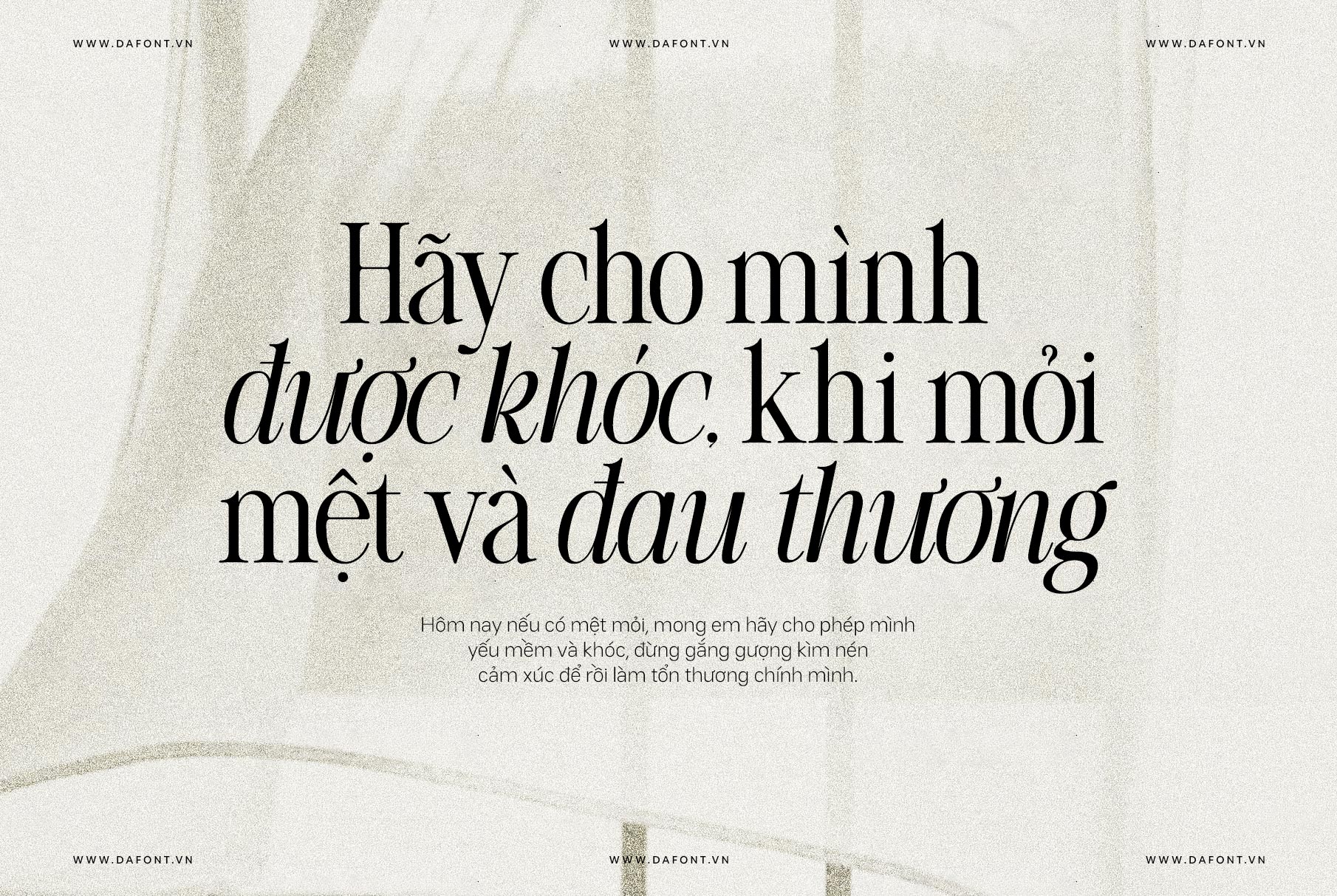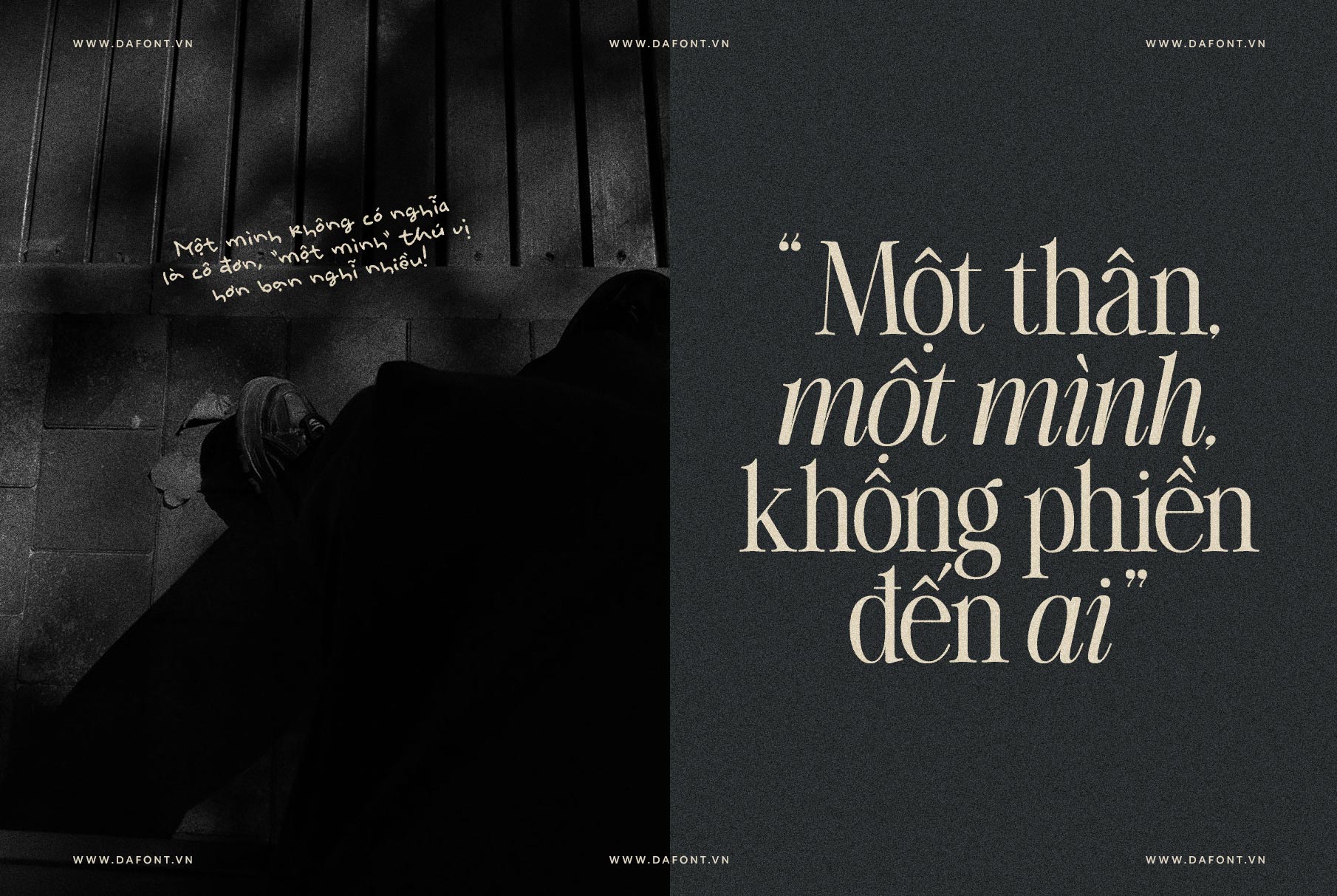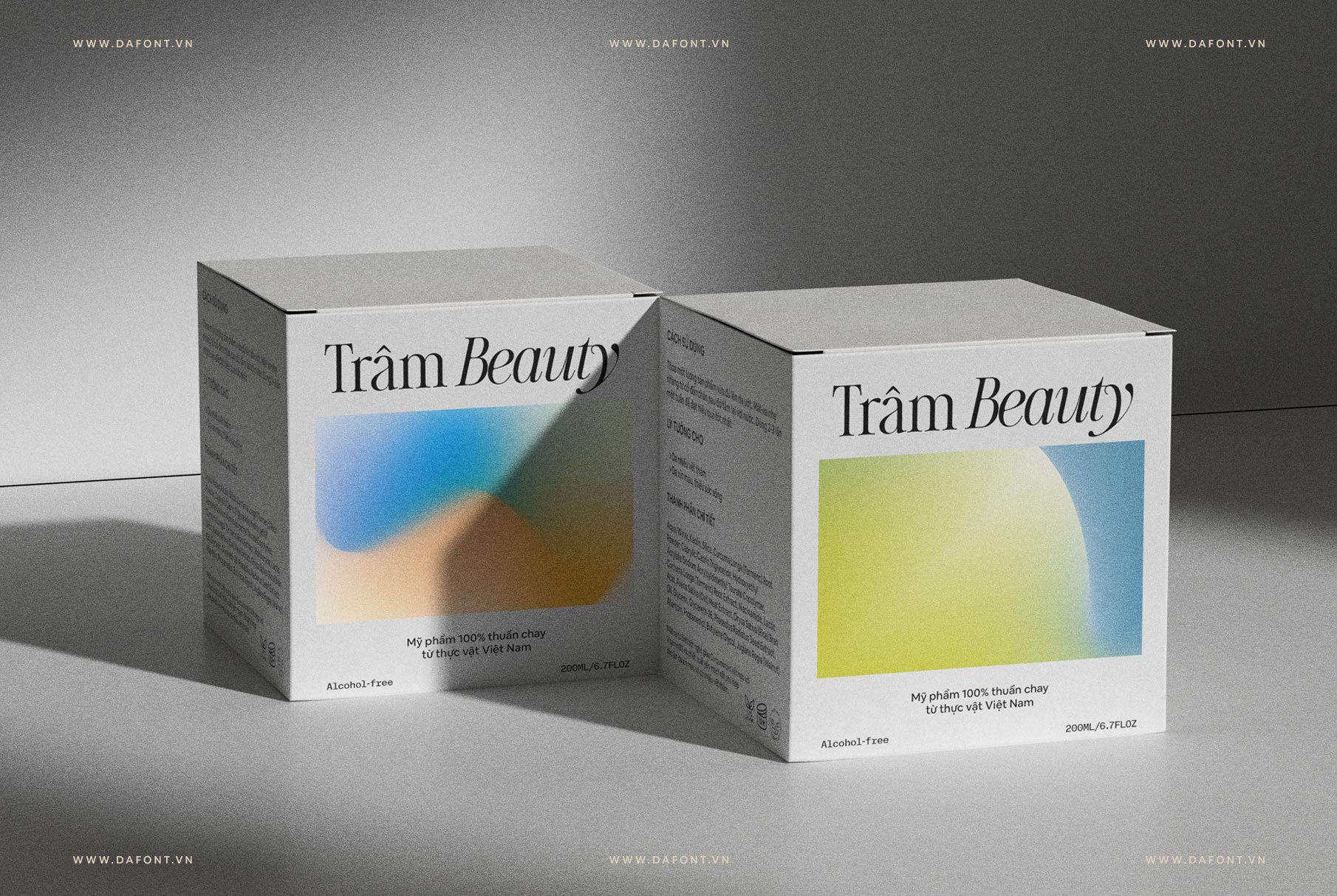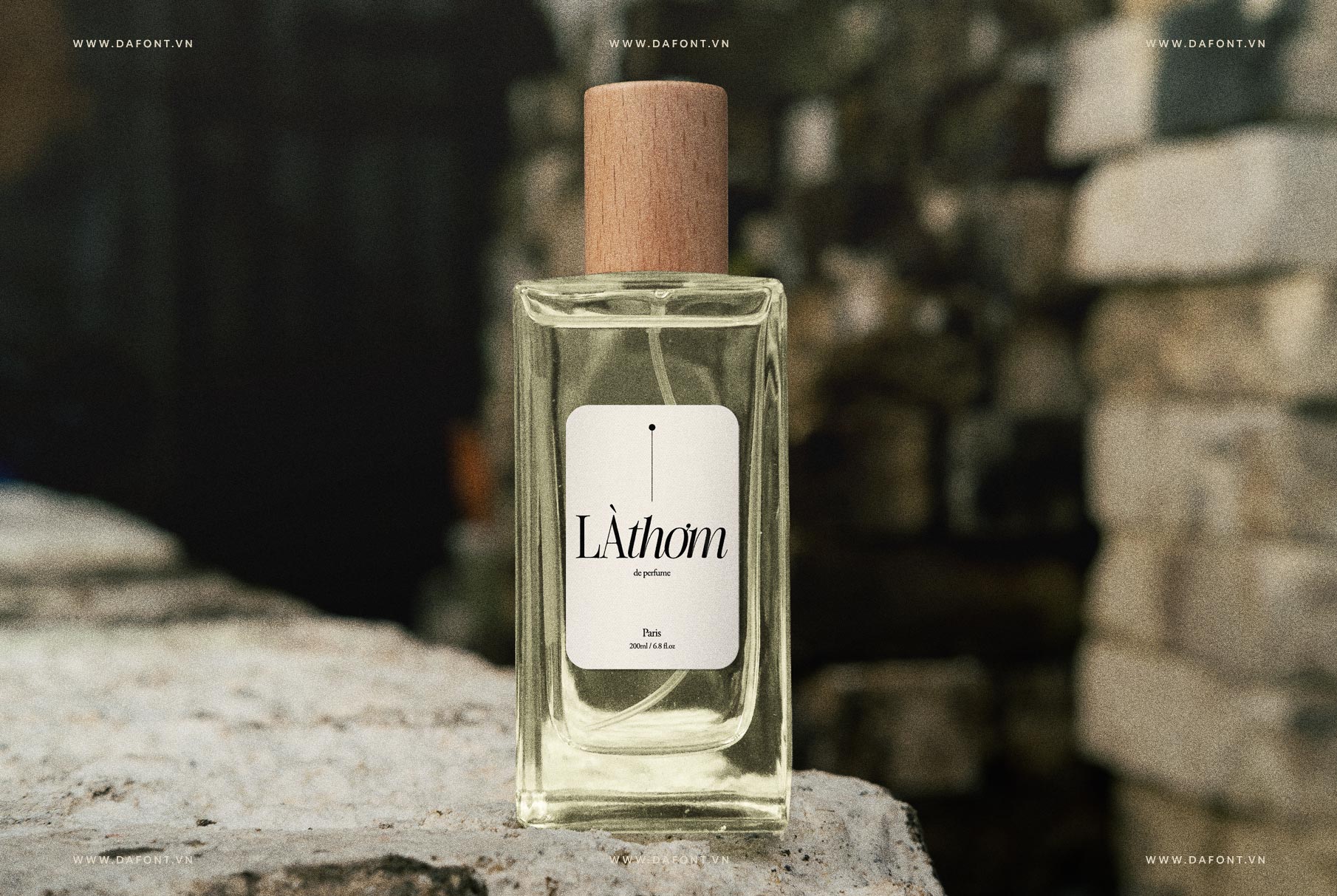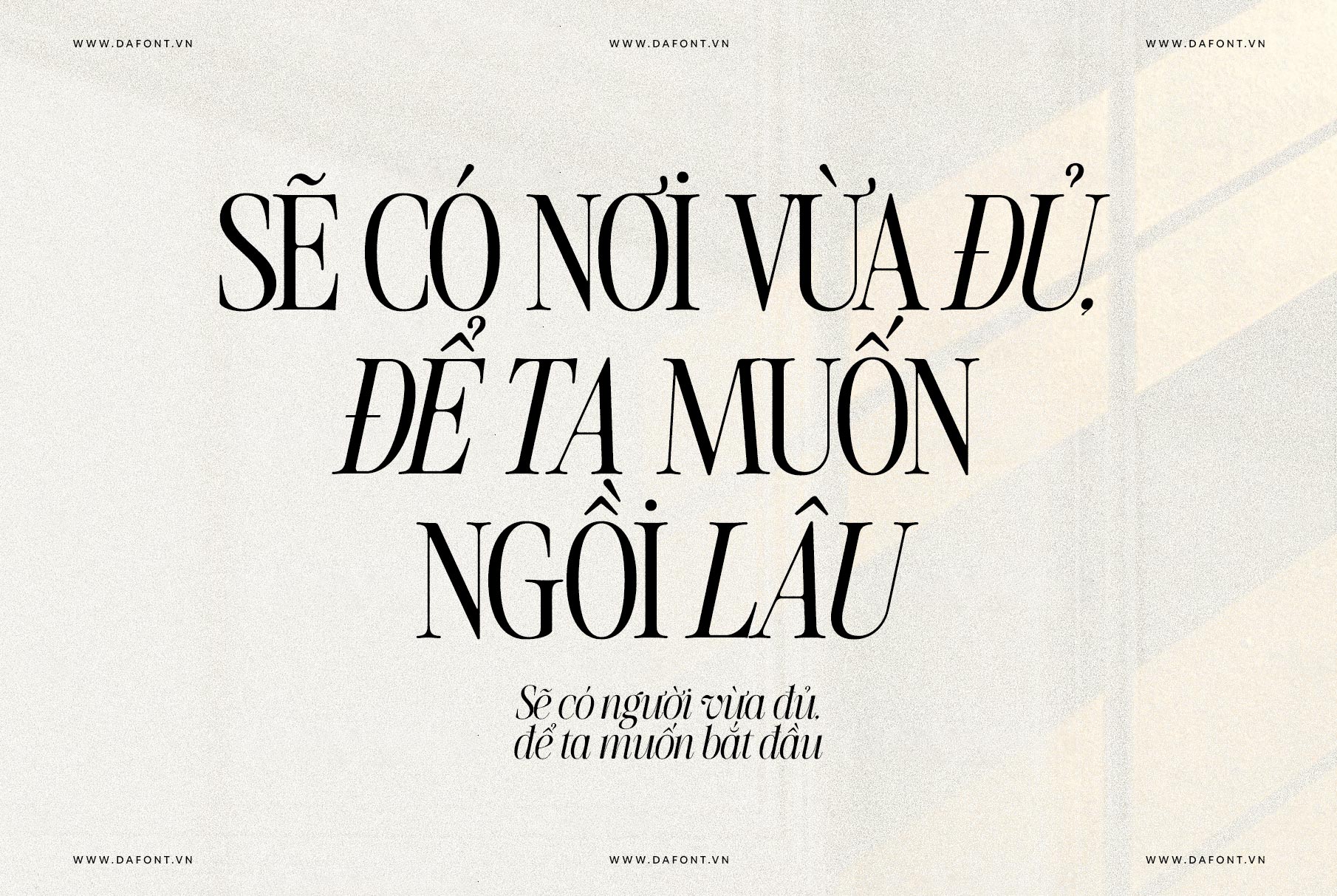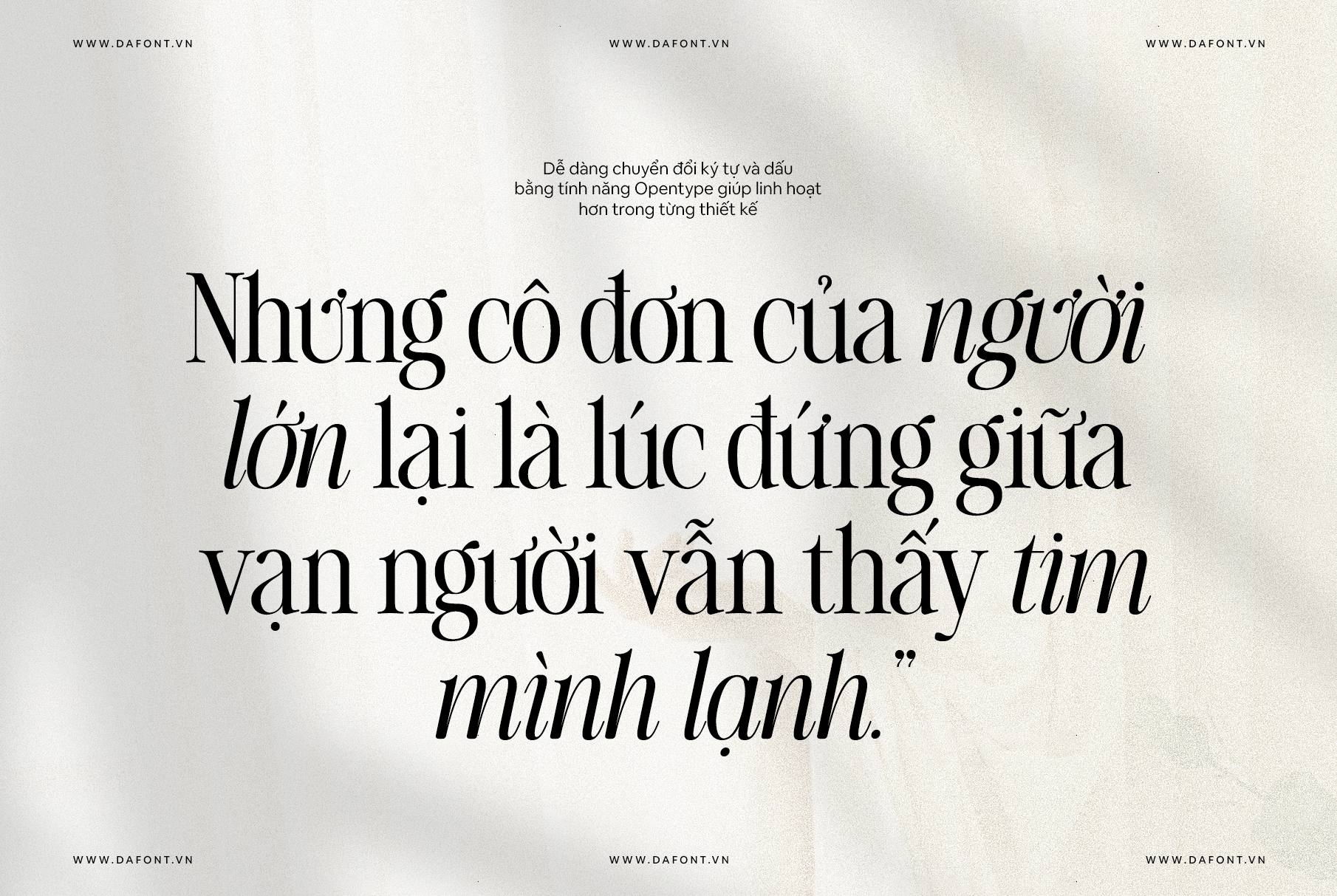
DFVN The Silver Editorial
Font chữ serif tinh tế cho thời hiện đại
DFVN The Silver Editorial không chỉ dừng lại ở vai trò là một font chữ; đây là sự kết tinh giữa những đường nét thanh thoát và phong cách vintage đậm chất đương đại. Những đường nét tinh tế và các chi tiết nghiêng độc đáo giúp font này nổi bật và tạo điểm nhấn trong bất kỳ dự án nào.
Đặc điểm nổi bật của DFVN The Silver Editorial
1. Nét đẹp vintage kết hợp hiện đại
The Silver Editorial được truyền cảm hứng từ những serif kinh điển của thập niên 80, mang lại nét độc đáo và sang trọng. Tuy nhiên, font này đã được tùy biến để phù hợp với thời đại số, gây ấn tượng nhờ những nét góc cạnh và tính linh hoạt.
2. Linh hoạt trong mọi loại thiết kế
Dù bạn đang thiết kế tạp chí, banner, hay website, The Silver Editorial mang lại khả năng biểu đạt mạnh mẽ trong mọi bố cục. Các chi tiết tinh tế trong font giúp đáp ứng đồng thời tính đọc hiểu và thẩm mỹ.
3. Nét chữ nghiêng nghệ thuật
DFVN The Silver Editorial là kiểu chữ hiển thị thu hút sự chú ý trong các tiêu đề. Tuy nhiên, nó vẫn có thể sử dụng liền mạch ở thân bài, đảm bảo khả năng đọc mà không làm mất đi tính cách.
Tuy nhiên, sức mạnh thực sự của nó nằm ở phiên bản in nghiêng. Chúng không chỉ nghiêng – chúng là một tác phẩm nghệ thuật riêng biệt, mang đến năng lượng năng động cho bất kỳ các thiết kế nào.
Tại sao bạn nên lựa chọn The Silver Editorial?
DFVN The Silver Editorial không chỉ là một font chữ, mà là một câu chuyện kết nối lịch sử và hiện đại. Việc kết hợp giữa tính thẩm mỹ cao và tính độc đáo khiến font này trở thành một công cụ có giá trị cho mọi nhà thiết kế.
Điểm nhấn Việt hóa DFVN The Silver Editorial
Font được làm mới lại dấu, kerning toàn bộ bao gồm cả những chữ cái thay thế, tính năng Opentype cũng được hỗ trợ. Dấu Ư, Ơ hoa và thường cũng được thiết kế 2 loại dấu để linh hoạt hơn trong việc sử dụng.
Ngoài ra, 1 số chữ cái của phiên bản in nghiêng (italic) cũng được tinh chỉnh lại bo tròn các góc cho phù hợp với tổng thể của font và chắc chắn sẽ đẹp mắt hơn.